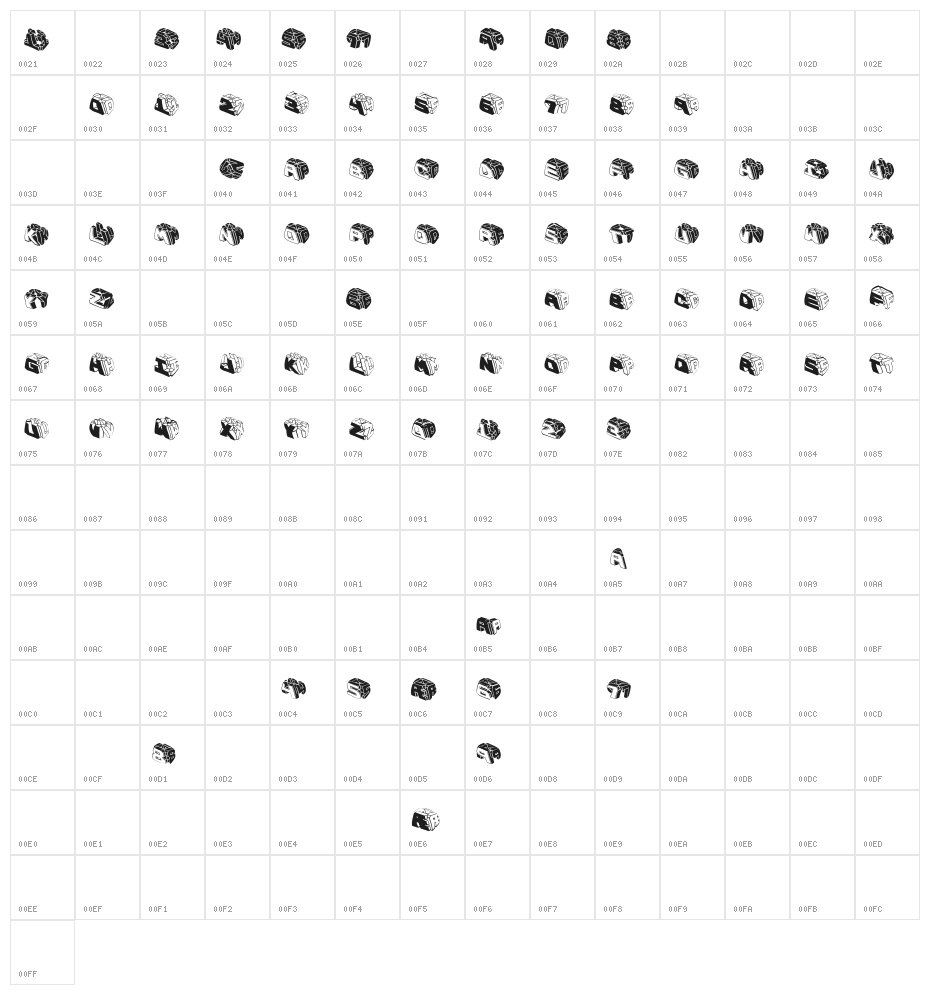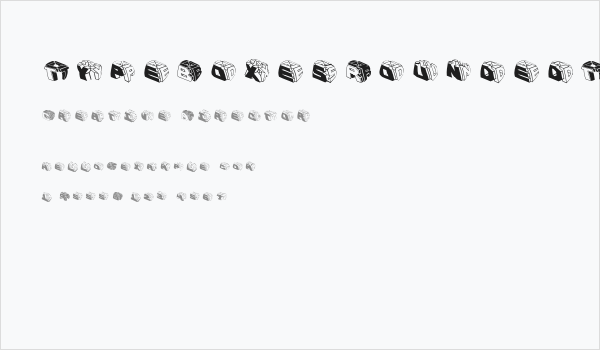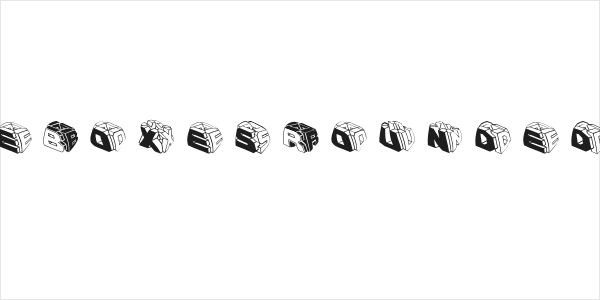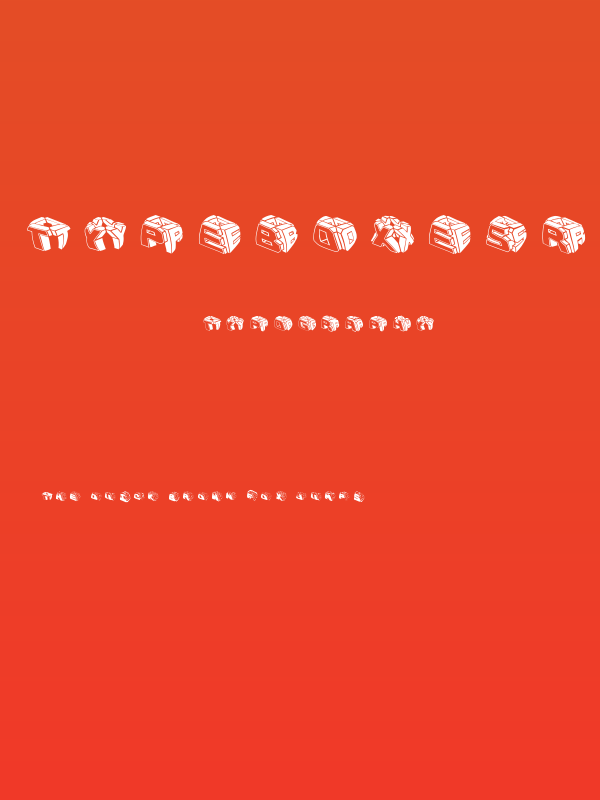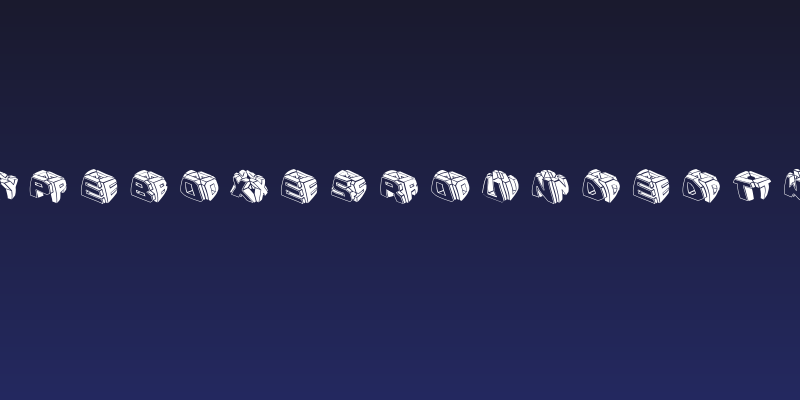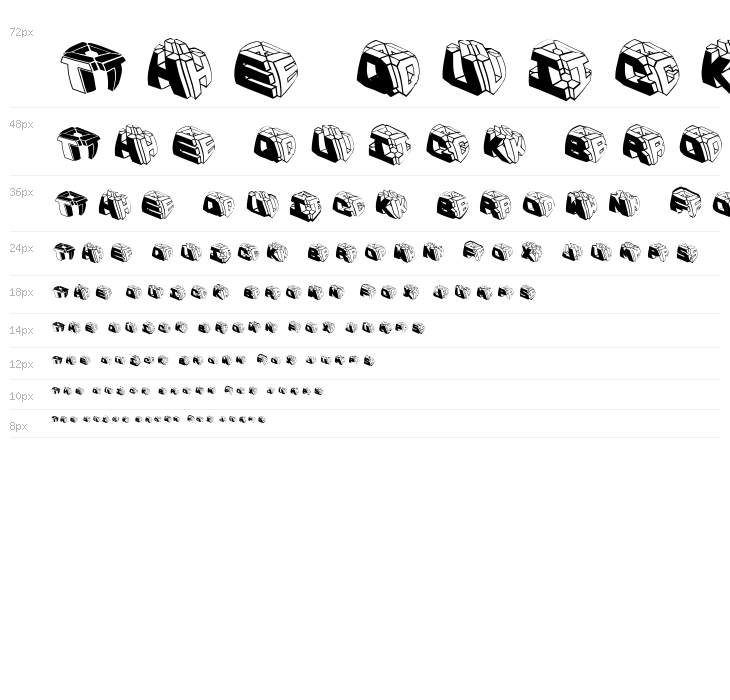
TypeBoxesRoundedTwo Font
| Caso de uso | Logos, Posters, Video game graphics |
| Proyectos propuestos | Ideal for creative projects such as posters, logos, and video game graphics where a modern and playful aesthetic is desired. |